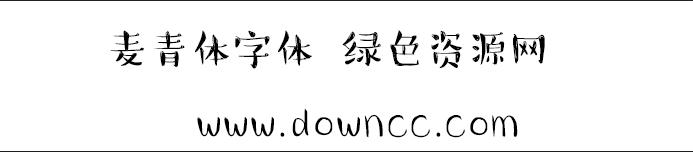
aunt麥青體
麥青體字體ttf字體風(fēng)格在眾多的字體中都能夠受到用戶們的喜愛,它的字體擁有一種獨(dú)特的美感,每一撇每一捺都十分圓潤(rùn),可以帶給你不錯(cuò)的視覺體驗(yàn)!
這款字體的獨(dú)特之處在于能夠讓你不斷的感受到舒適的體驗(yàn),字體風(fēng)格十分圓潤(rùn),并不鋒利,讓你在聊天交友過(guò)程中以及所需的適當(dāng)媒體制作中都能夠運(yùn)用!
3、麥青體字體行筆圓轉(zhuǎn)。線條勻凈而長(zhǎng)。呈現(xiàn)出莊嚴(yán)美麗的風(fēng)格。